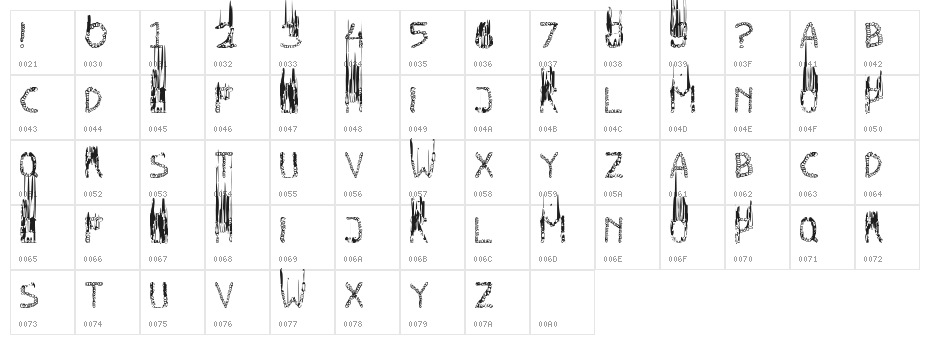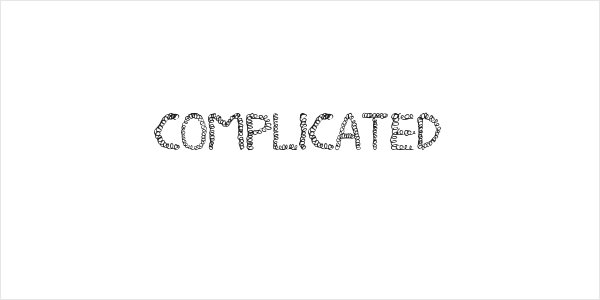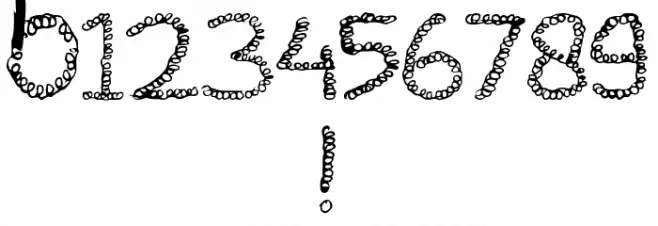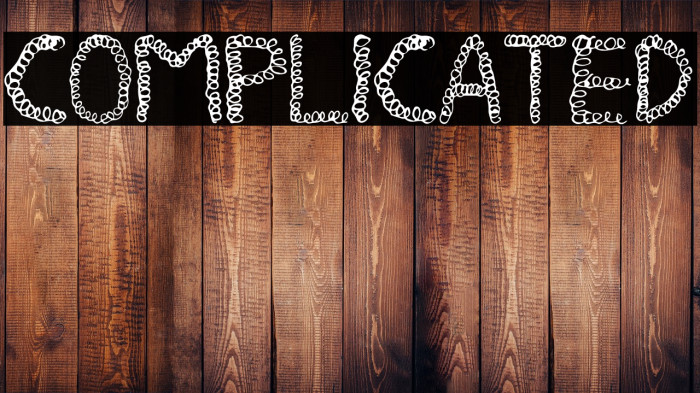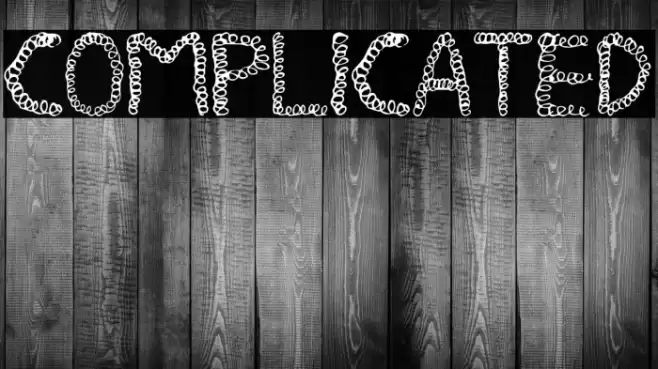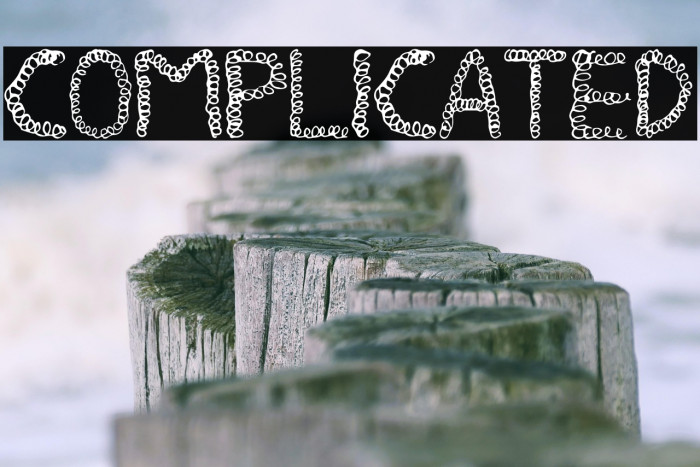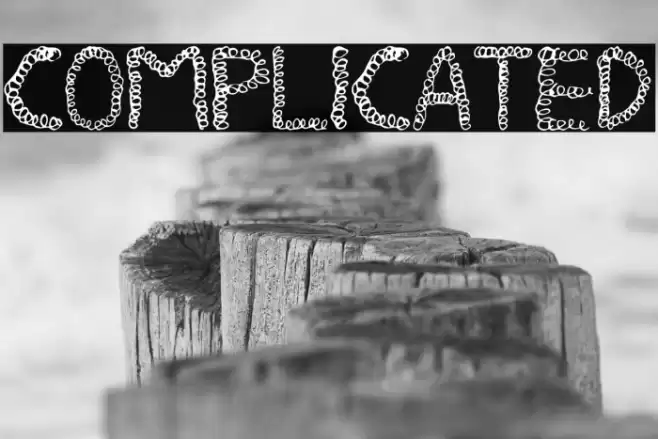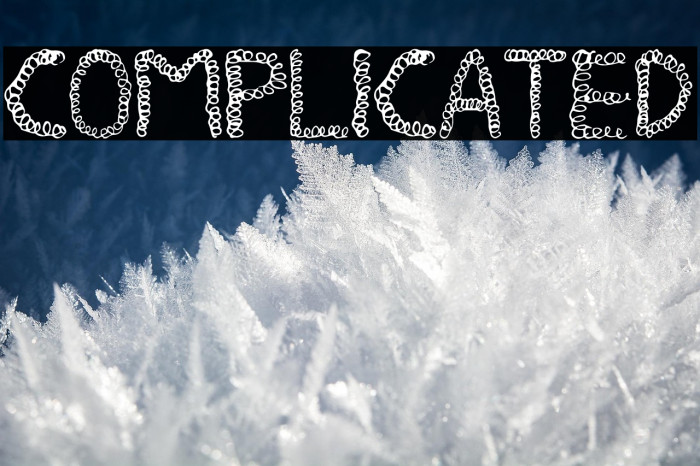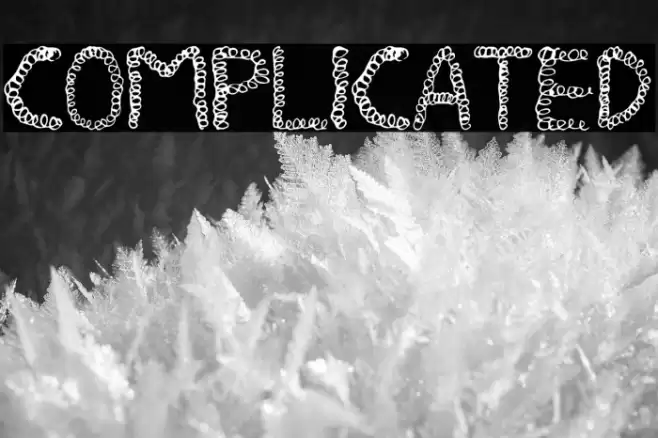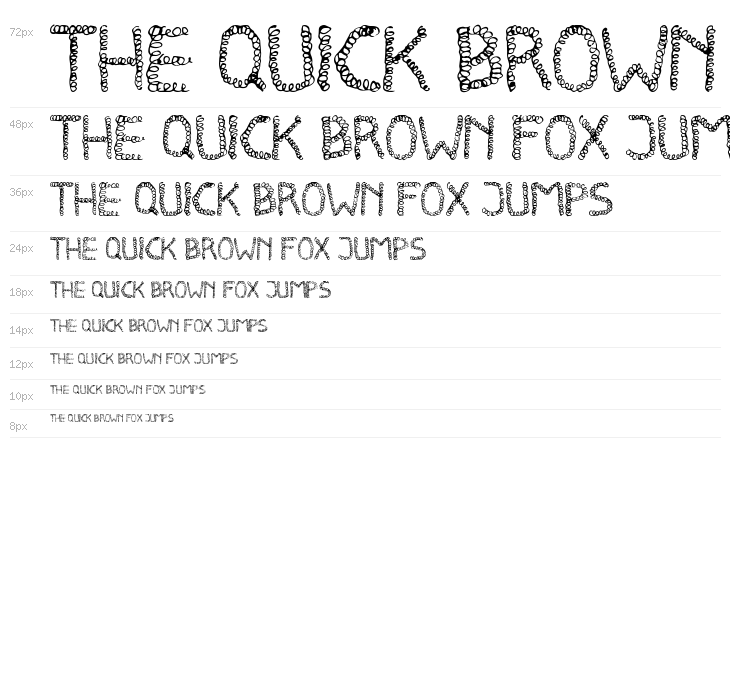
COMPLICATED Font
| Cas d'utilisation | Logos, Headlines, Artistic projects |
| Projets proposés | Ideal for children's books, creative invitations, playful branding, and artistic projects. |